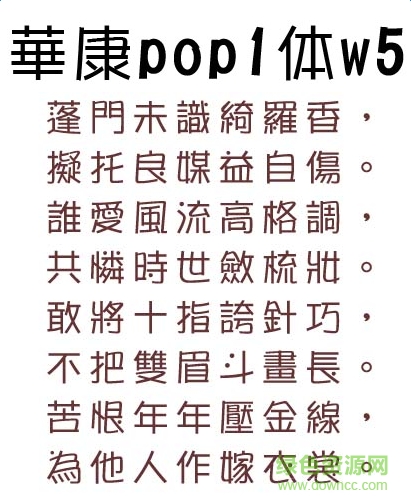
華康POP1是一套廣告專用字體,字形效果和形象明確,讓人難忘,中和的外形,讓它使用范圍非常廣,常用于宣傳、海報、招牌,作為廣告用的標(biāo)題非常合適。
這是一套設(shè)計師依多年從事廣告工作經(jīng)驗所開發(fā)出來的廣告專用字型,刻意的安排使整套字型效果與形象十分明確,令人一見難忘,而其中和的外形色彩,也使它在使用領(lǐng)域上十分廣泛。